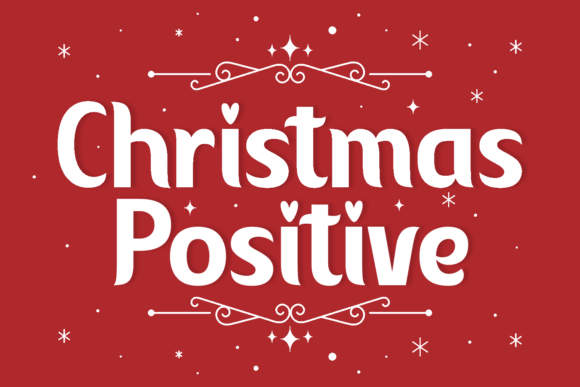
Christmas Positive
適切なデザイン要素を見つけるのは難しい場合がありますが、Christmas Positiveは作品を即座に引き立てる優れたコレクションを提供します。
POD(オンデマンド印刷)製品、結婚式の招待状、またはソーシャルメディアのグラフィックを作成している場合でも、Christmas Positiveは理想的です。